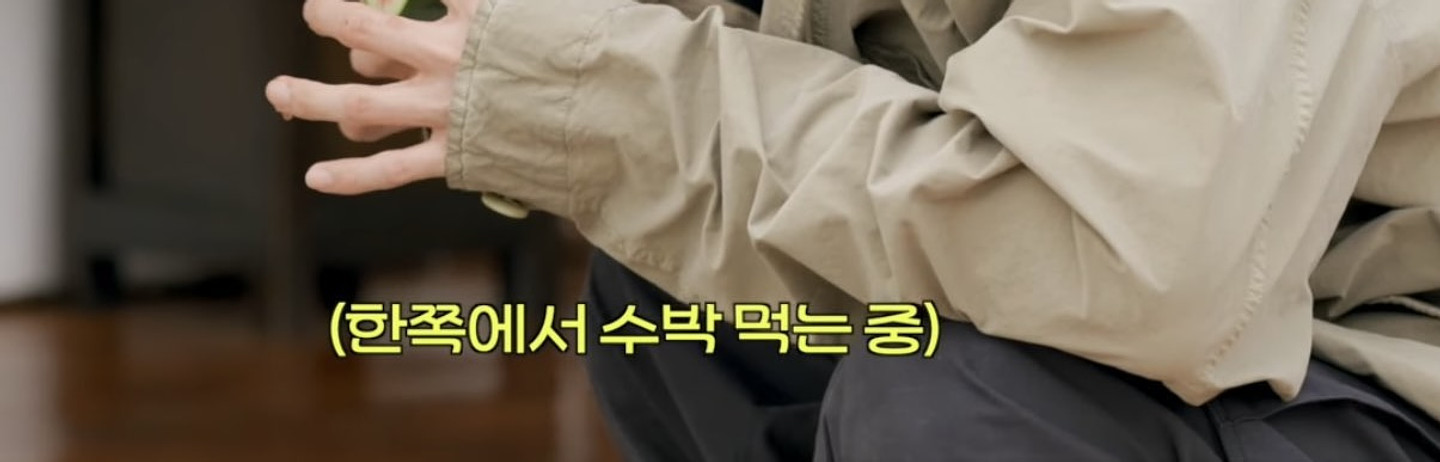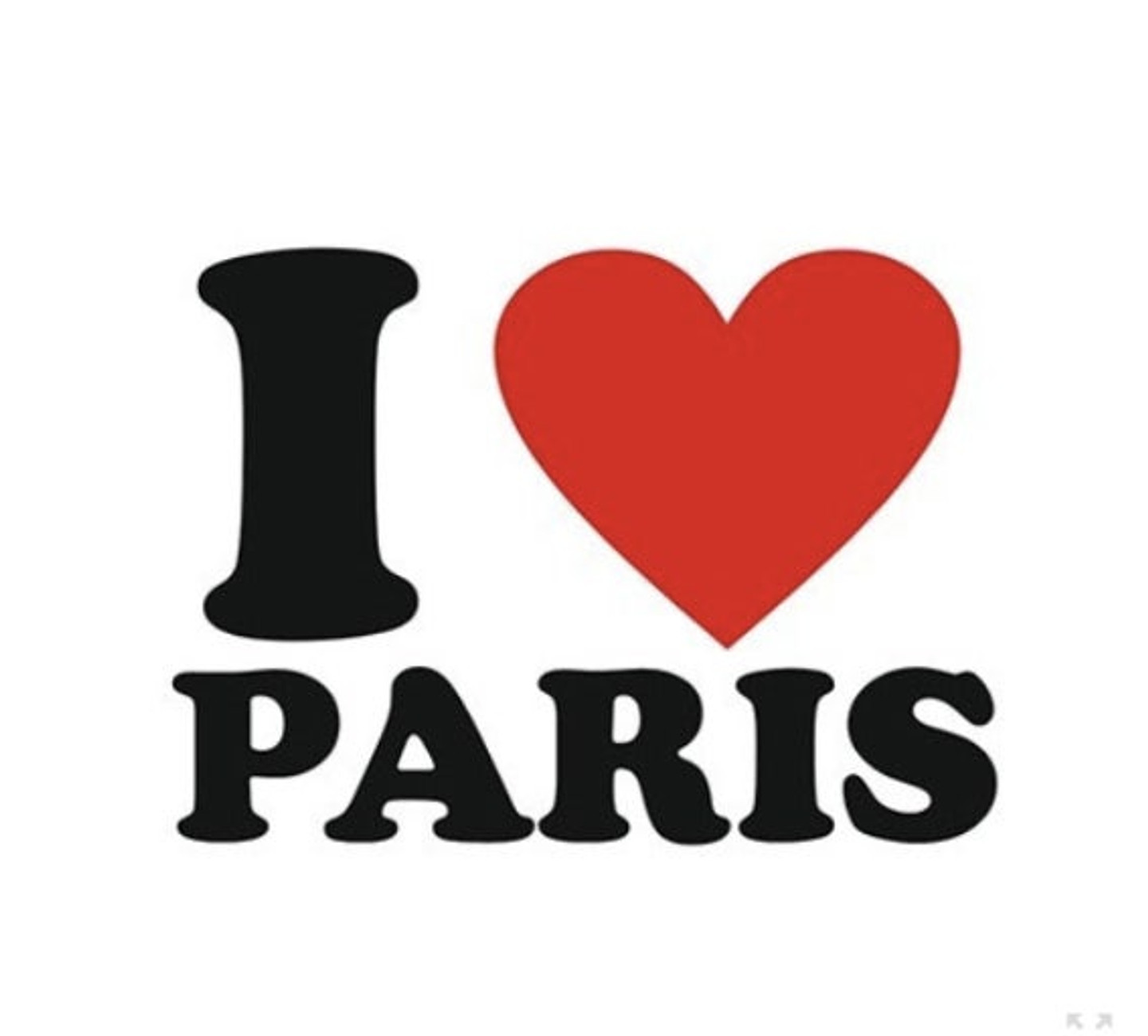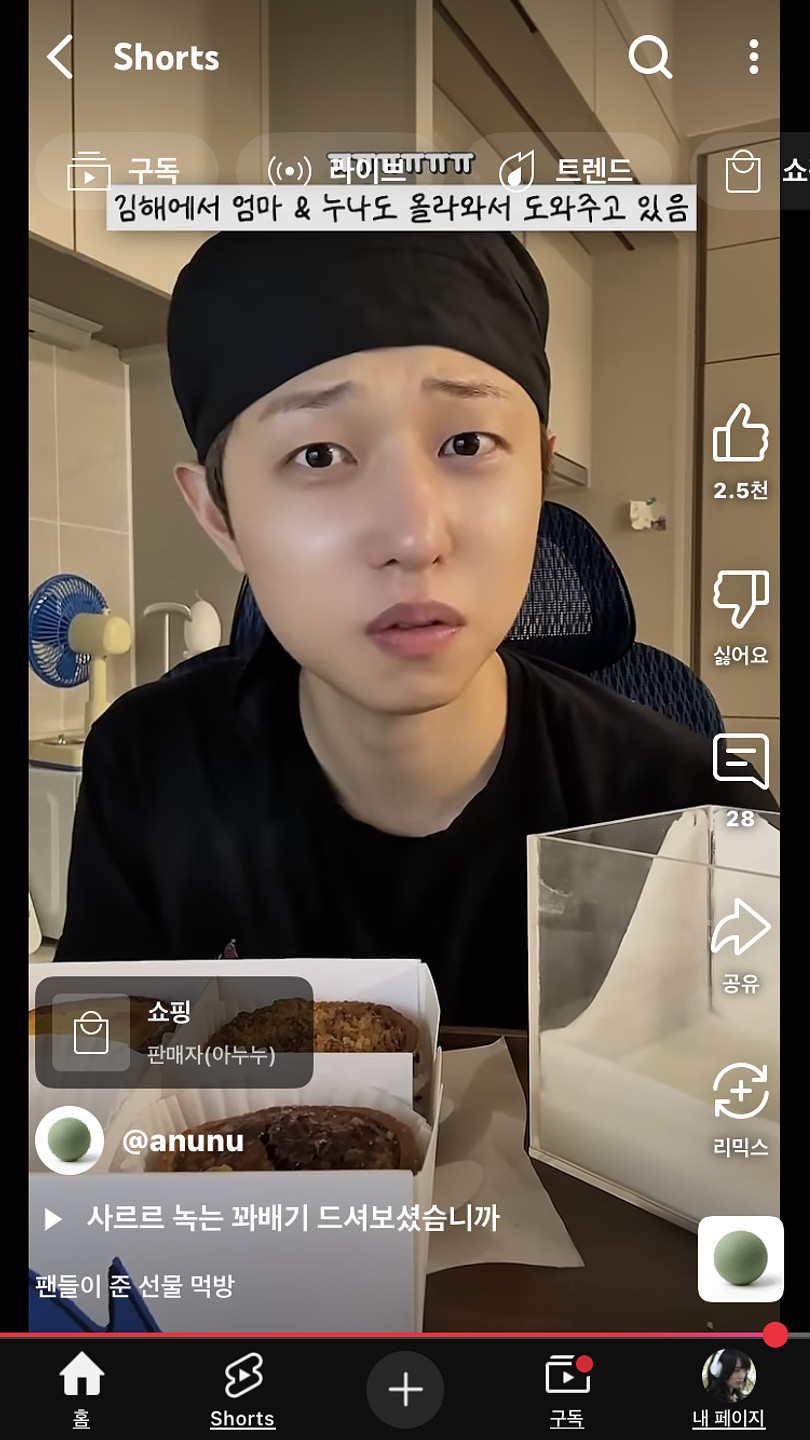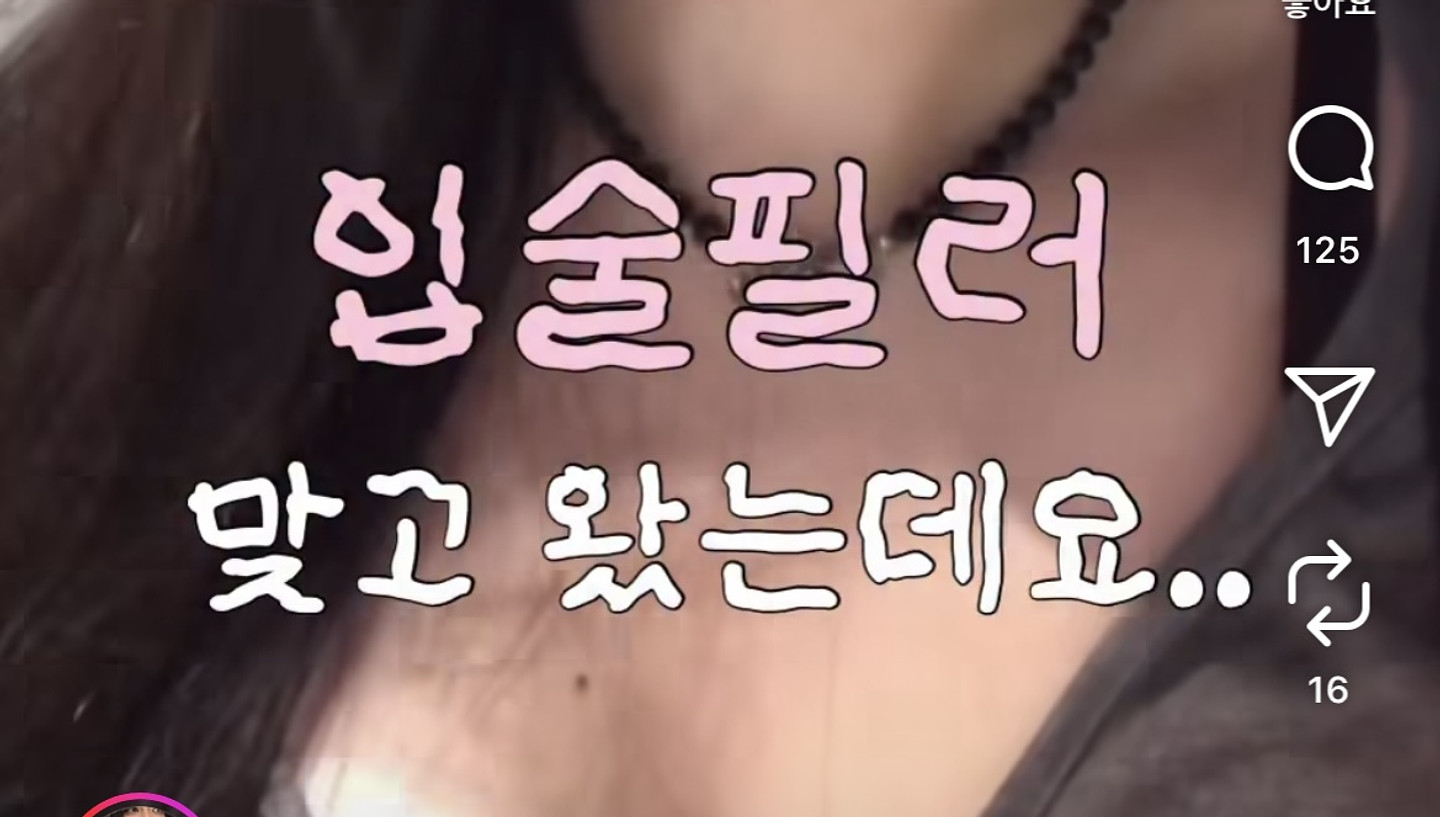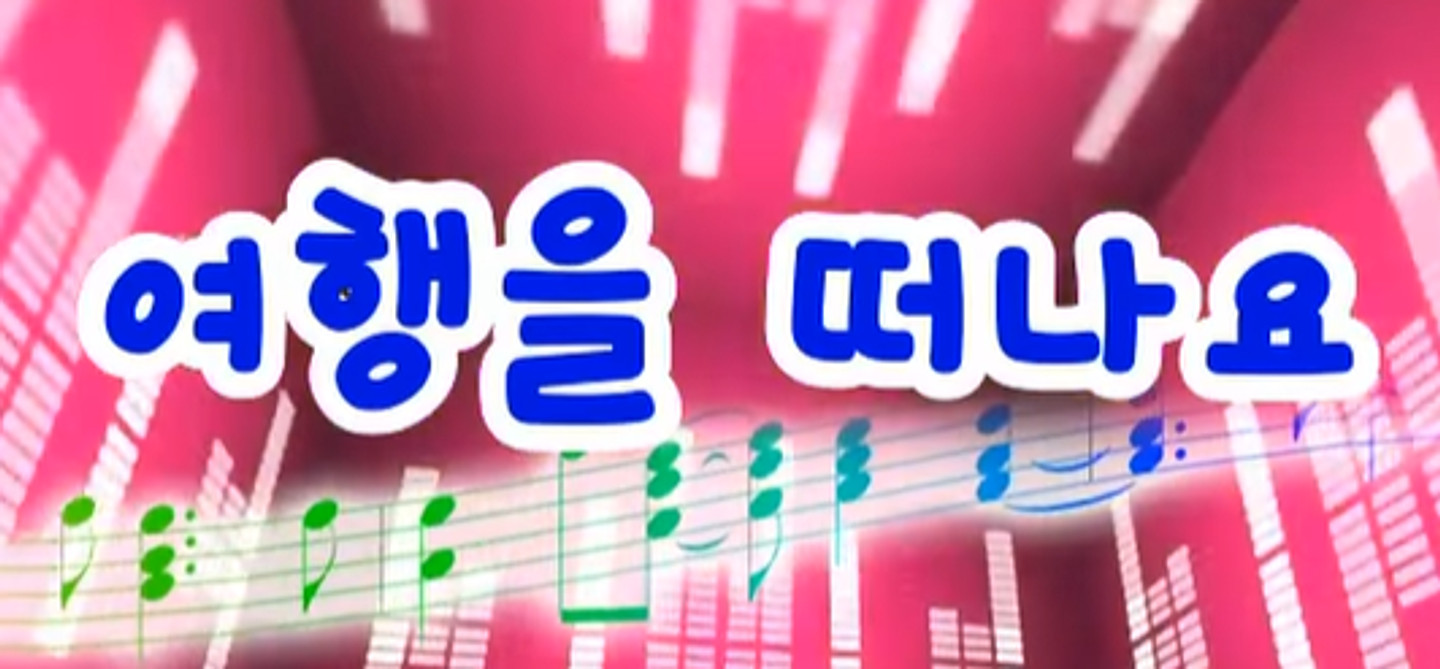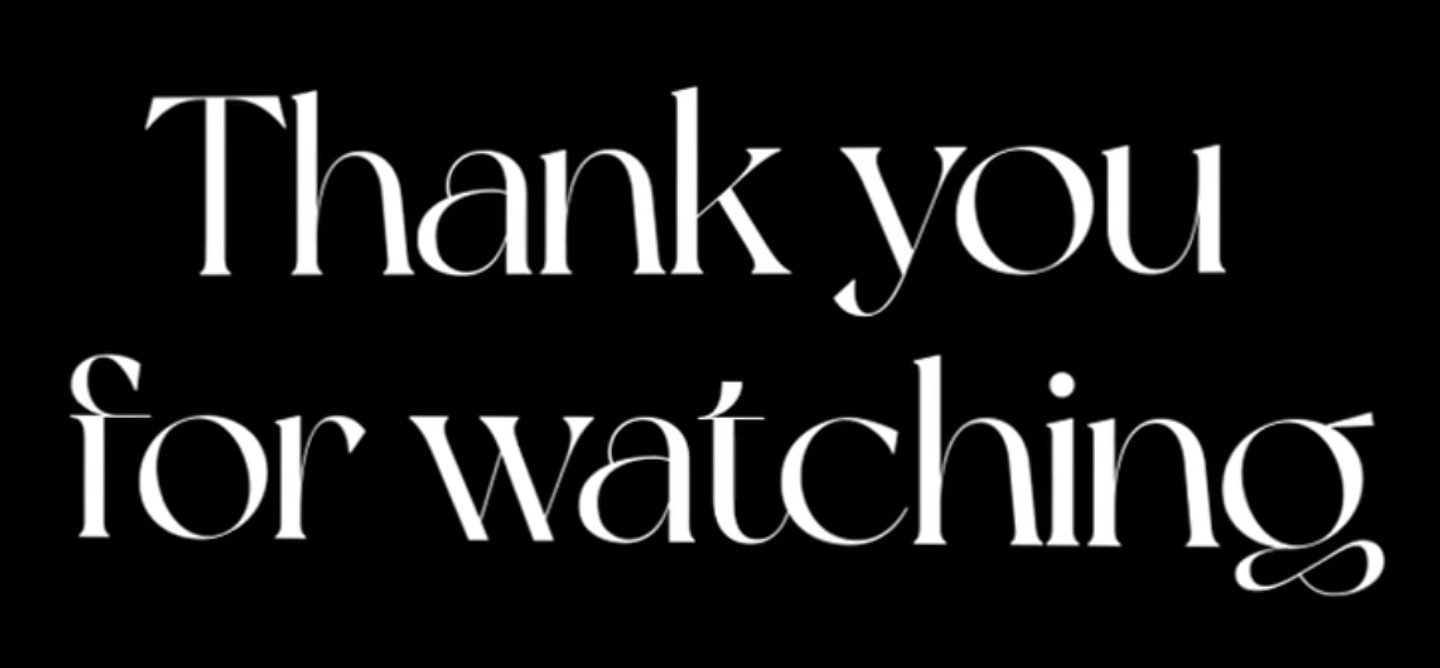
무슴글씨체인거요 ㅠ
이 폰트 아시면 알려주세용~~^^
MEMOIRE 글자 폰트 뭔지 아시나요ㅠㅠ 제작해야되는데 아시는 분 제발 알려주세요...
이건 어떤 폰트인가요?
무슨 폰트죠? 본 것 같은데 참 예쁘네요
지지플래닛님 유튜버에서 나오는 폰트가 궁금합니다
혹시 이거 무슨 폰트 일까여!!
한글과 영문 모두 같은 폰트인것 같습니다. 무슨 폰트일까요?
이 폰트 이름이 뭔가요?
이 폰트이름을 알수있을까요ㅠㅠㅠ 폰트찾기해도 안나옵니다ㅜ
폰트 부탁드려요!
이 폰트 뭘까요? 넘 궁금합니다!
폰트 부탁드립니다^^
영어 폰트 인데 많이 깨졌네요 포토샵 사용할때 썼던건데 뭔지 모르겠습니다 영어가 다 뭉개져서 나와서요
이게 무슨 폰트일까요?
무슨 글씨체일까요..?
제목 서체가 궁금해요!
해당 폰트는 무슨 폰트일까요.,
폰트 어떤 폰트일까요? 뒤에 검은색으로 깔리는 두께효과는 겹쳐서 낸거일거 같긴한데 베이스로 사용된 폰트가 뭔지 궁금합니다
이 폰트 궁금해요
'ㄹ' 이 지그재그로 특이한 이 폰트 이름 뭔가요?
이 폰트는 무슨폰트인가요??
폰트 궁금합니다!!
해당 폰트가 궁금합니다
이거 무슨 폰트인가여 ..?
이 폰트 궁금해요..!!
프로젝트 헤일메리 책 표지 폰트 알려주세요
여기에 쓰인 일본어 폰트, 영어 폰트 꼭 알고싶어요 ㅠㅠ
요 폰트 뭔지 아시는분!! 너무 궁금합니다아 ㅠㅠ
안녕하세요 : ) 혹시 해당 폰트도 어떤 글씨체인지 알 수 있을까요 ㅠㅠ 항상 감사합니다 ❤︎ 좋은 하루 되세요!
안녕하세요 ! 혹시 해당 폰트는 무슨 글씨체인지 알 수 있을까요 ㅠㅠ 감사합니다 •ᴗ•
안녕하세요 ! 혹시 해당 폰트는 무슨 글씨체인지 알 수 있을까요 ?? 감사합니다 •ᴗ•
안녕하세요 : ) 혹시 해당 폰트 어떤 글씨체인지 알 수 있을까요..❤︎
기본폰트가 뭔지 알려주세요
무슨폰트일까요 알려주세요:)
폰트 알려주세요?
어떤 폰트일까요옹.. MOODA 라는 일기장 엡에서는 Xiaolai SC 라고 나옵니다..!!
폰트 이름을 알고 싶어
이 폰트가 무슨 폰트일까요??? 영어라 잘 모르겠네요... Ai한테 물어봐도 묘하게 다른 폰트만 얘기해주는거같아요
푸치코뉴. 오늘은 내가 대신 질문할 거다뉴. 아, 내가 대신 질문하는 이유는 푸유쨩이 귀찮다고 해서 나 푸치코가 대신 질문하는 거니까 내 말에 토 달진마라뉴. 이 폰트 아는 사람 답 좀 해라뉴. 폰트가 너무 이쁘다고 푸유쨩이 쓰고싶다더라뉴. 그럼 부탁한다뉴. 바이바이뉴.
무슨 폰트일까요? 메인타이틀 ㄹ 표현 너무 좋은데
맨 위 자연에 성성을 다합니다 노란색 유럽형 목조펜션 숫자 각 글씨체가 궁금합니다.
무슨 폰트인지 궁금해요!
폰트 어떤건지 궁금해여!!
폰트명 찾아주세요ㅠ!
요즘 많이 쓰는 이 폰트 무슨 폰트인가요
크포님 폰트
대원미디어 VHS 에 들어갔던 공익광고 문구입니다. "한편의 비디오, 사람의 미래를 바꾸어 놓을수도 있습니다." 부분 서체를 알고 싶습니다.
이 폰트가 무엇인지 알수 있을까요? a발레리나 폰트와 비슷하게 생겼는데 아니더라구요. 아시는분 답변부탁드려요.
이폰트무엇일까요
이 폰트가 뭔지 알 수 있을까요?
이 글꼴 제발 알려주세요
이 폰트 무슨 폰트인가요?
이 폰트 뭘까요??
이 영상 폰트가 뭐예요?
한글이랑 영문 둘 다 폰트 알수있을까요???